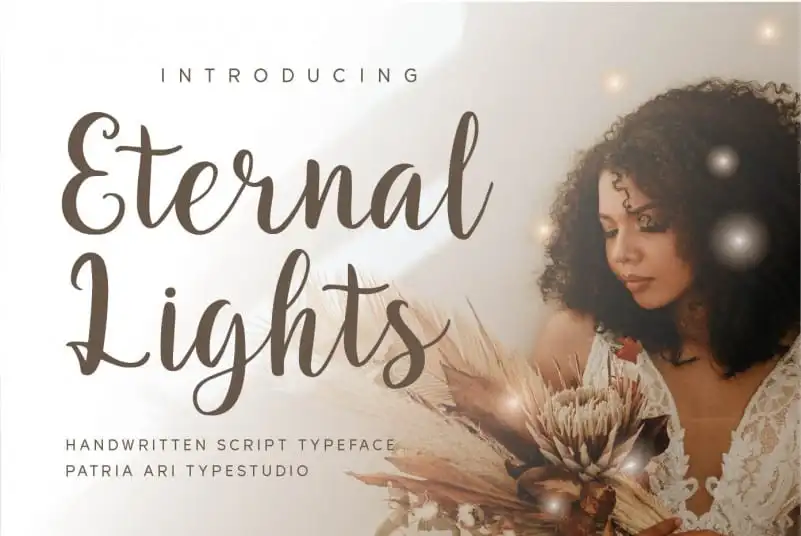
Eternal Lights Script Font – Download Grátis
Eternal Lights Script Font é uma deliciosa fonte cíliar que traz detalhes curtos e encantadores, perfeita para projetos que exigem personalidade única e a mão do artesão. Esta elegante fonte foi especialmente criada com designers em mente, oferecendo alternativas suaves aos caracteres padrões. Perfeito para uso em criações de marca, logotipos, convites de casamento, postagens no Instagram, anúncios, embalagens de produtos, design de produtos, rótulos e até mesmo cartas de convidados ou materiais de decoração. Seja você um designer gráfico, uma agência de branding ou uma empresa de comunicação que busca achar personalidade em seus projetos digitais, Eternal Lights Script Font é a escolha perfeita para iluminar sua identidade visual.